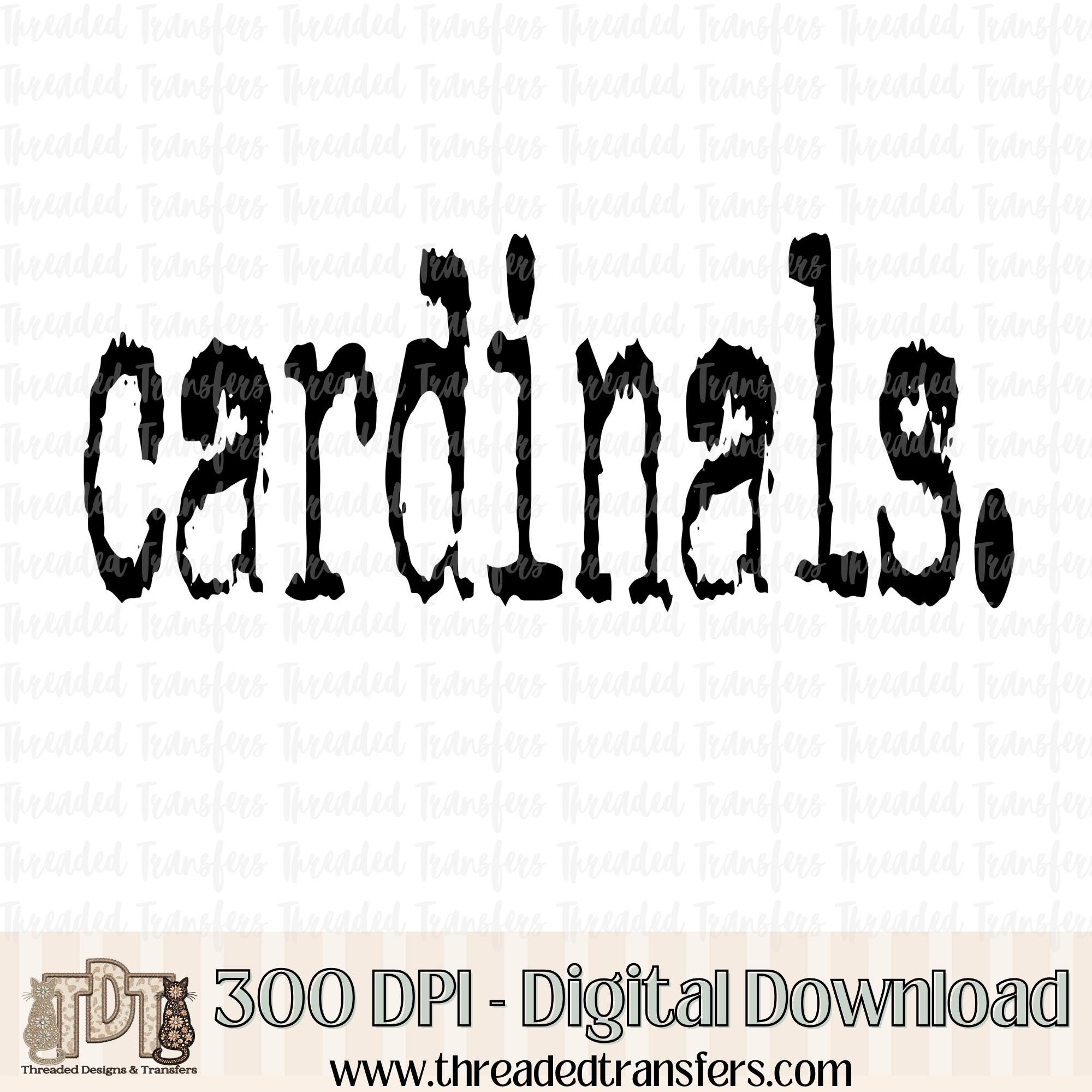
Tipografía de Mascota Cardinals PNG | Diseño de equipo deportivo desgastado | Descarga digital para Sublimación y DTF
Demuestra el orgullo por tu equipo con este potente diseño de tipografía de la mascota Cardinals, pensado para makers, artesanos y pequeños negocios que buscan un gráfico deportivo llamativo y con excelente calidad de impresión. Descarga digital PNG en alta resolución (300 DPI) con un acabado envejecido de inspiración vintage, perfecto para prendas escolares, outfits de día de partido y merchandising de fans. Ideal para sublimación y DTF, ofrece resultados nítidos y vibrantes en camisetas, hoodies, sudaderas, jerseys, bolsas tote, tazas y más.
- Acabado desgastado para un look tendencia con vibra de school spirit
- Perfecto para deporte, equipos escolares y apparel de fans